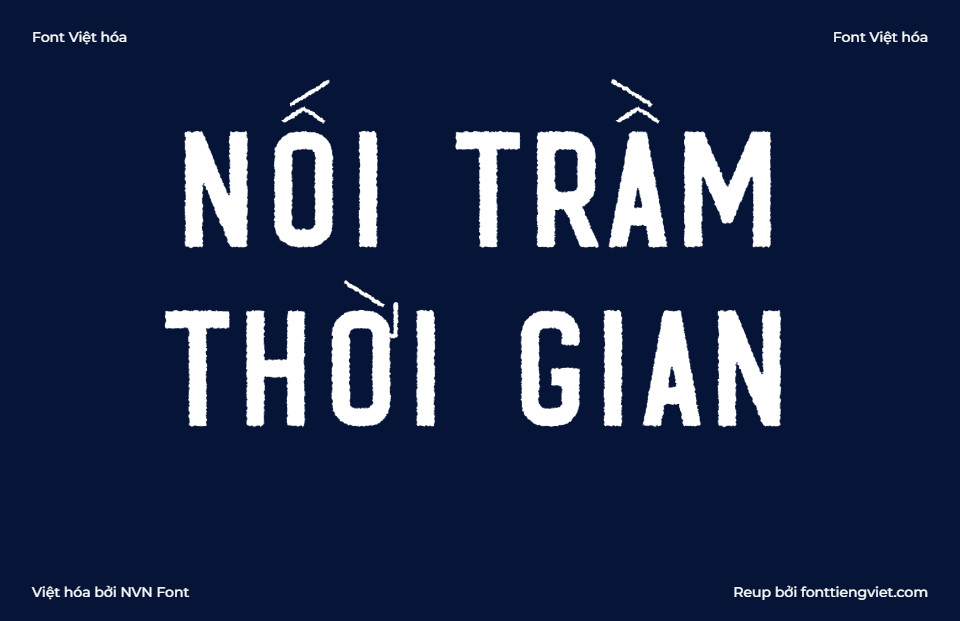
Font Việt hoá NVN Southland Sans Distort Reg
Giới thiệu về Font Việt hoá NVN Southland Sans Distort Reg
Trong thế giới thiết kế đồ họa hiện đại, việc lựa chọn một bộ phông chữ phù hợp đóng vai trò quyết định đến sự thành công của một tác phẩm truyền thông. Font Việt hoá NVN Southland Sans Distort Reg là một cái tên đang thu hút sự chú ý lớn từ cộng đồng sáng tạo nhờ phong cách độc đáo và tính ứng dụng cao. Đây là một phiên bản tùy chỉnh đầy cá tính, mang lại hơi thở mới mẻ cho các dự án thiết kế chữ tiếng Việt. Khi tìm kiếm một giải pháp Font Miễn Phí chất lượng, người dùng thường ưu tiên những bộ font đã được xử lý dấu kỹ lưỡng như NVN Southland Sans Distort Reg để đảm bảo văn bản không bị lỗi hiển thị.
Đặc điểm thiết kế của Font Việt hoá NVN Southland Sans Distort Reg
Đúng như tên gọi của mình, bộ phông chữ này sở hữu những đường nét “Distort” – nghĩa là có sự biến dạng nghệ thuật đầy chủ ý. Các ký tự không tuân theo quy tắc cứng nhắc của các dòng Sans Serif truyền thống mà được nhấn nhá bằng những nét cắt, độ dày mỏng không đồng nhất, tạo nên hiệu ứng thị giác mạnh mẽ. Font Việt hoá NVN Southland Sans Distort Reg mang phong cách hiện đại, pha chút bụi bặm của đường phố nhưng vẫn giữ được sự tinh tế cần thiết. Nhờ việc Việt hóa bài bản, các dấu câu tiếng Việt được sắp xếp vị trí cân đối, hài hòa với cấu trúc tổng thể của từng chữ cái, giúp người dùng dễ dàng truyền tải thông điệp mà không gặp bất kỳ rào cản kỹ thuật nào.
Ứng dụng thực tế của Font Việt hoá NVN Southland Sans Distort Reg trong giáo dục và thiết kế
Mặc dù có vẻ ngoài phá cách, Font Việt hoá NVN Southland Sans Distort Reg lại rất thân thiện và phù hợp với nhiều mục đích khác nhau, đặc biệt là trong môi trường học đường. Các bạn học sinh, sinh viên có thể sử dụng font chữ này để thiết kế bìa tiểu luận, làm slide thuyết trình hay sáng tạo các ấn phẩm cho câu lạc bộ trường học. Sự phá cách của font chữ giúp các nội dung giáo dục trở nên sinh động và lôi cuốn hơn, tránh gây cảm giác nhàm chán cho người xem.
Sử dụng trong truyền thông và mạng xã hội
Bên cạnh giáo dục, Font Việt hoá NVN Southland Sans Distort Reg còn là lựa chọn hàng đầu cho các nhà sáng tạo nội dung trên mạng xã hội. Với khả năng gây ấn tượng thị giác ngay từ cái nhìn đầu tiên, phông chữ này cực kỳ thích hợp để làm tiêu đề video, ảnh đại diện YouTube hay các bài đăng Instagram mang tính nghệ thuật. Cấu trúc Sans Serif giúp chữ dễ đọc ngay cả trên màn hình điện thoại nhỏ, trong khi chi tiết biến dạng tạo nên dấu ấn thương hiệu cá nhân rõ nét.
Kết luận về bộ Font Việt hoá NVN Southland Sans Distort Reg